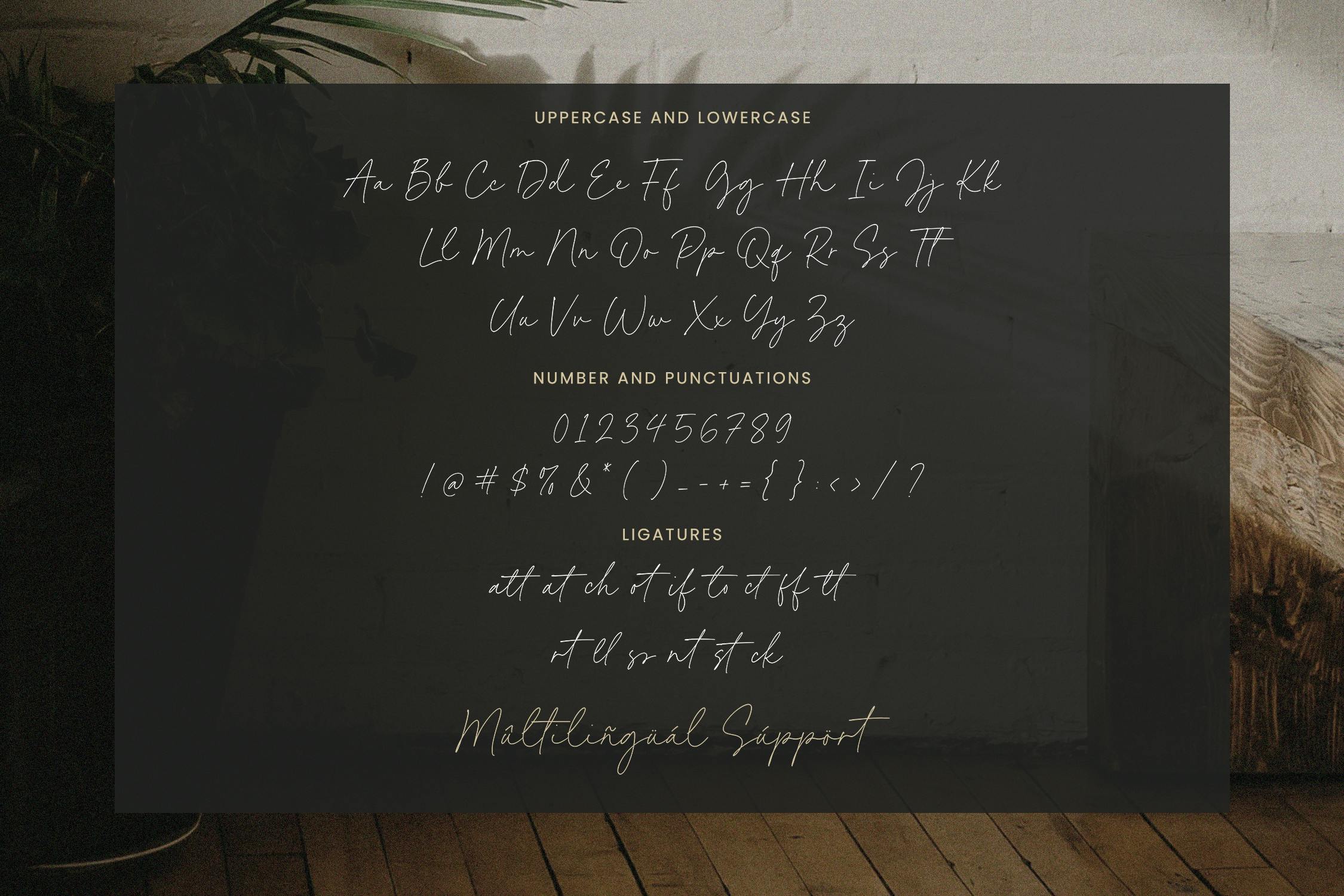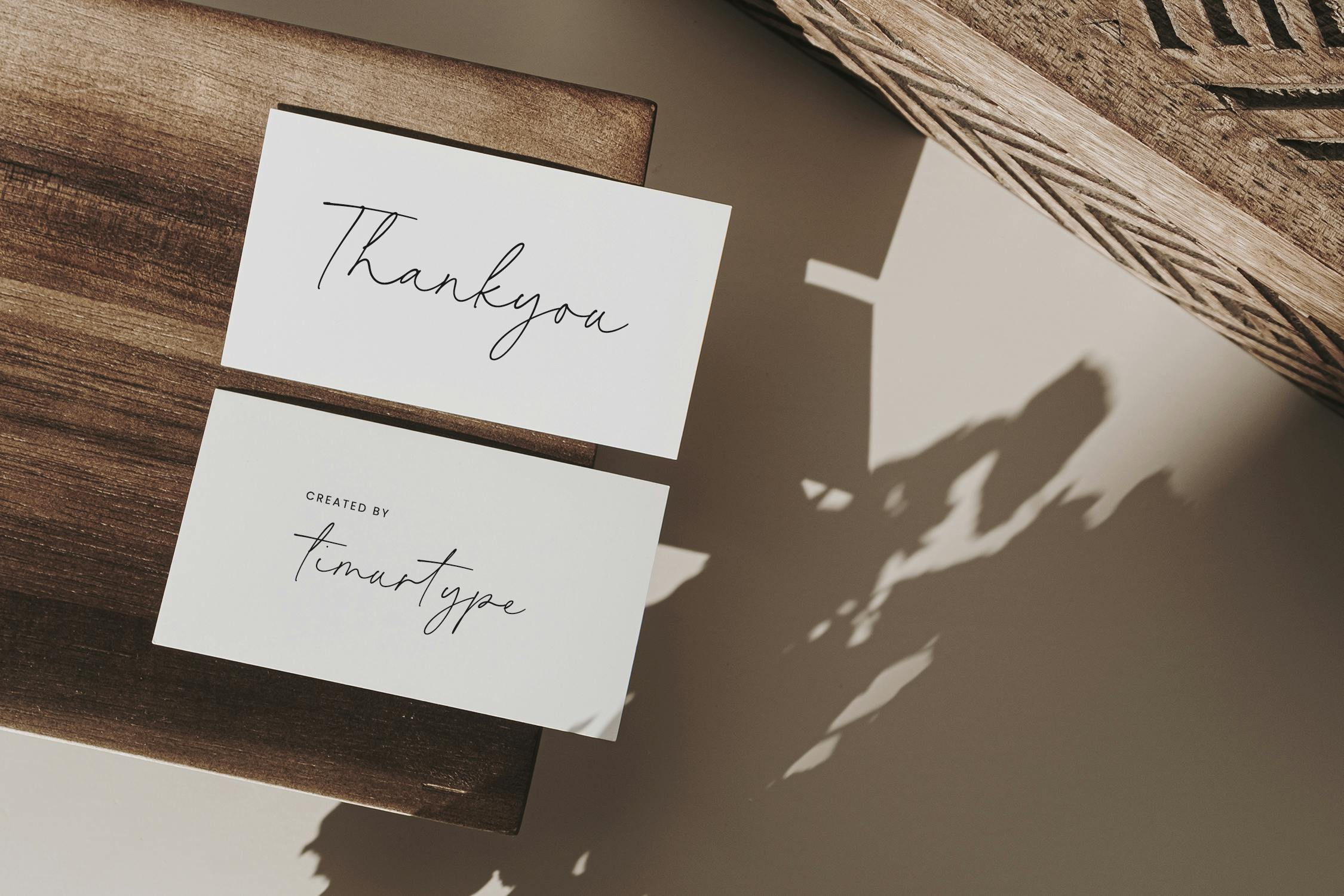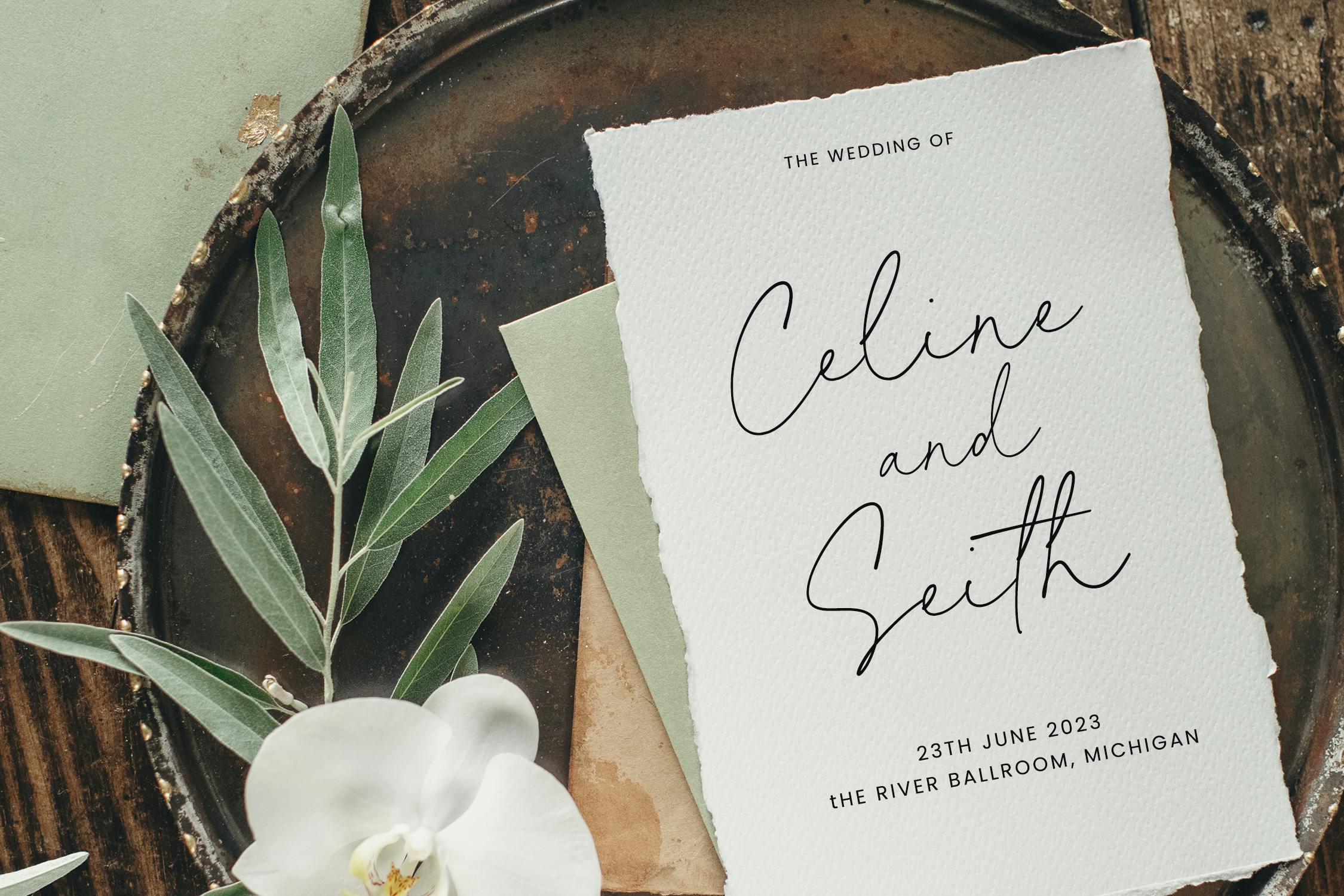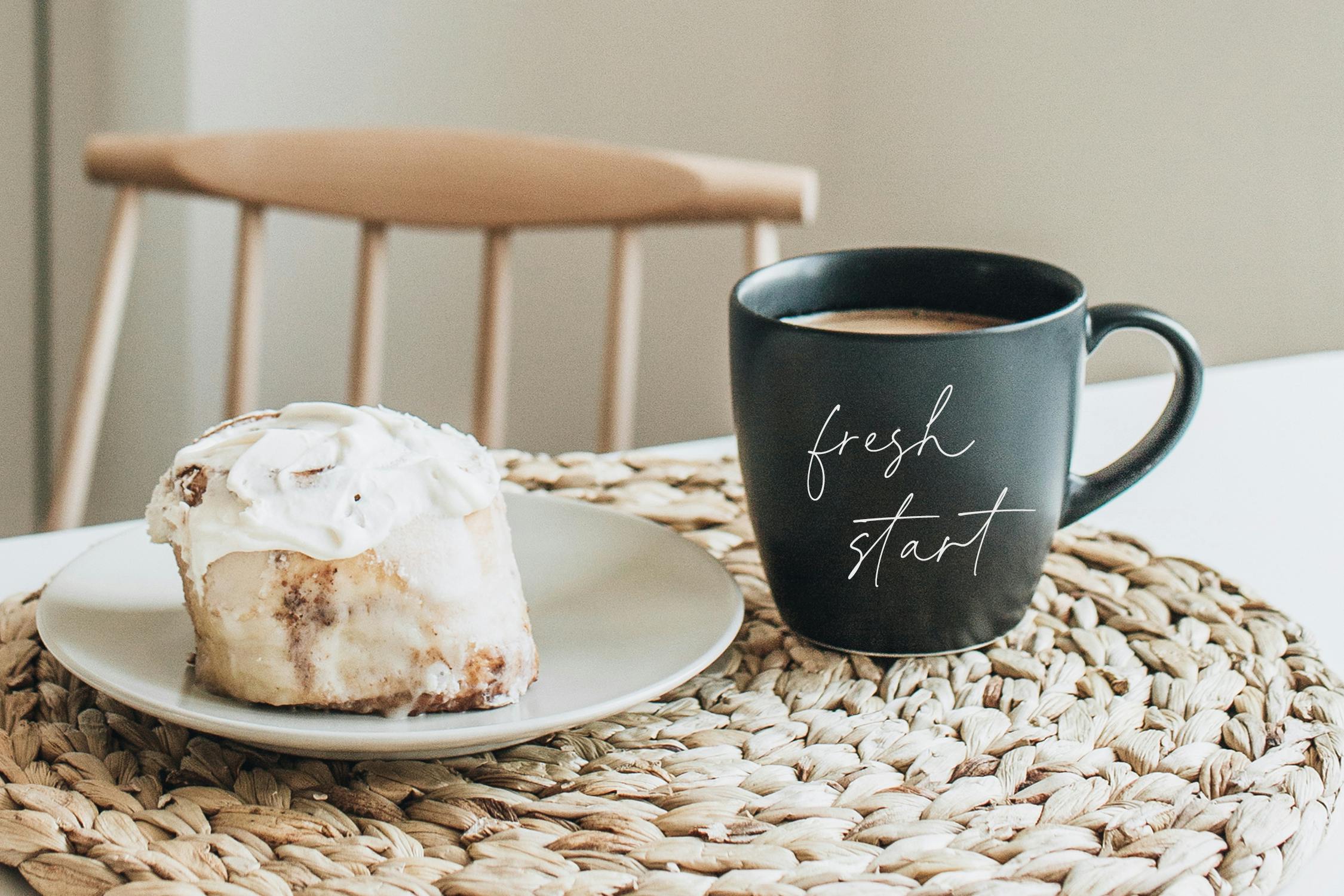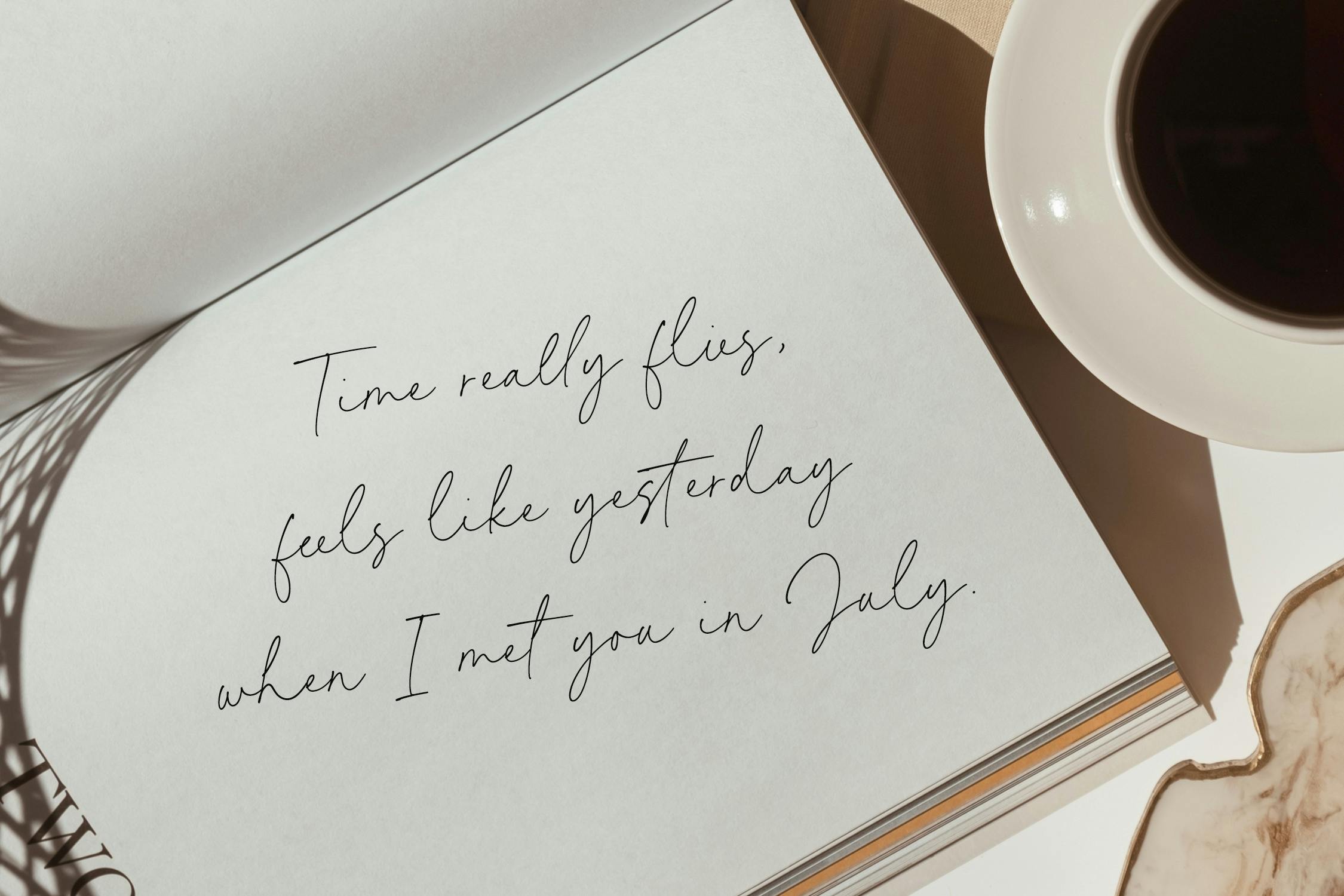
به معرفی فونت Kimberly Paradise میپردازیم. این فونت اسکریپت دستی با دقت بالا طراحی شده و مخصوص شما خلق شده است.
فونت Kimberly Paradise برای بستهبندی محصولات، پروژههای برندینگ، مجلات، رسانههای اجتماعی، عروسی یا فقط برای بیان کلمات بر روی پسزمینه بسیار مناسب است.